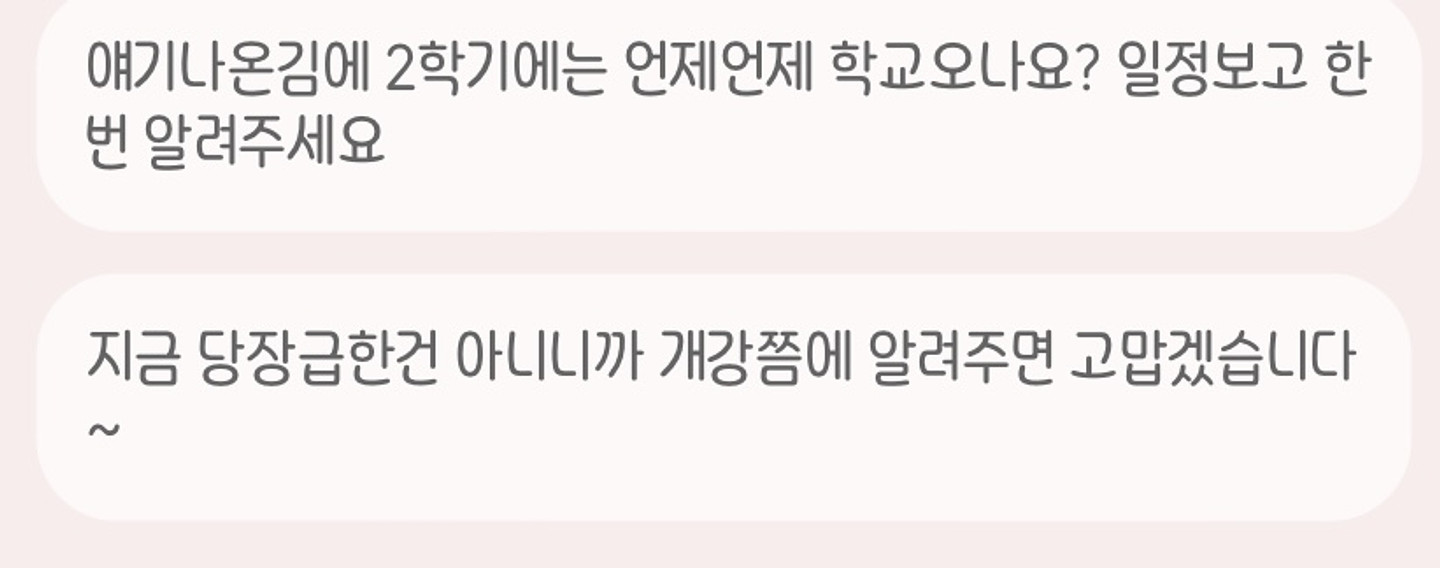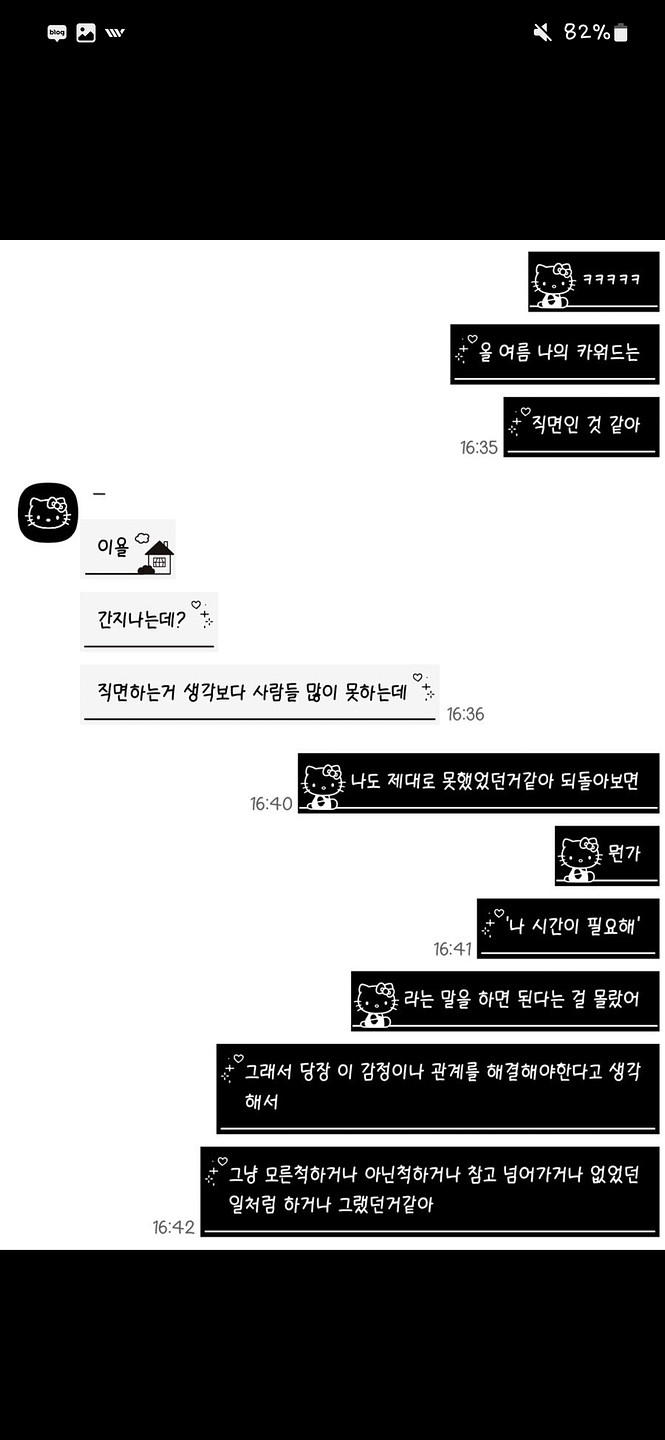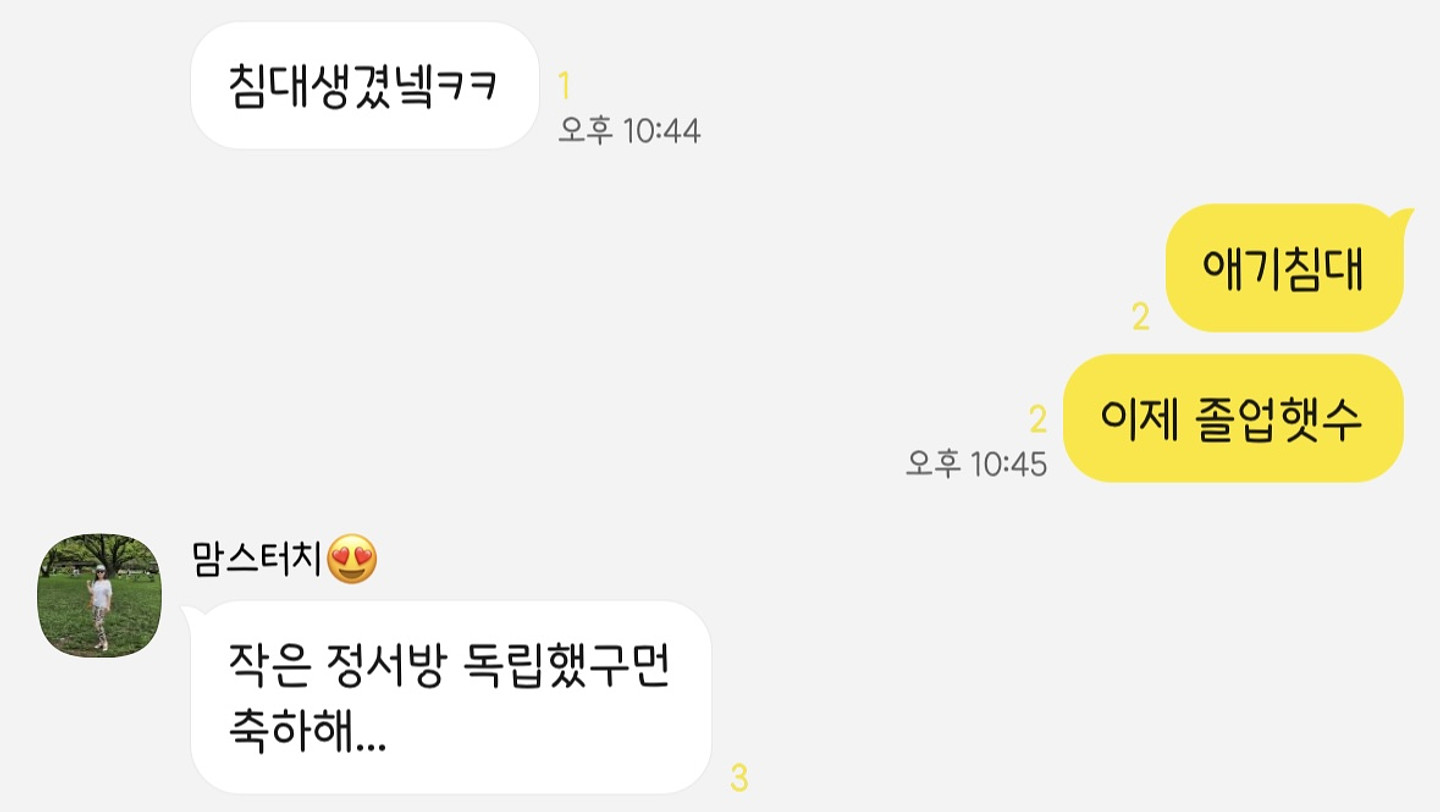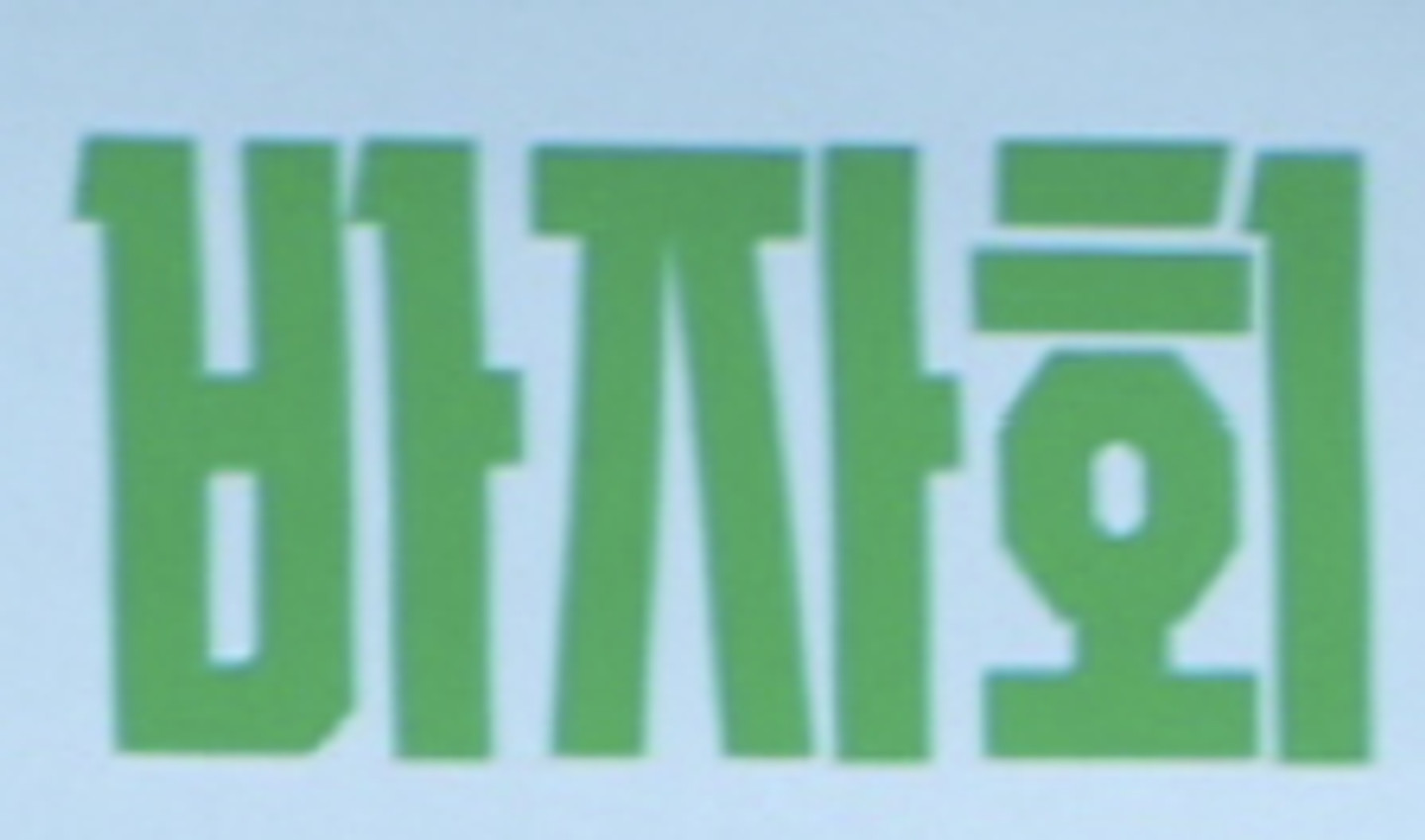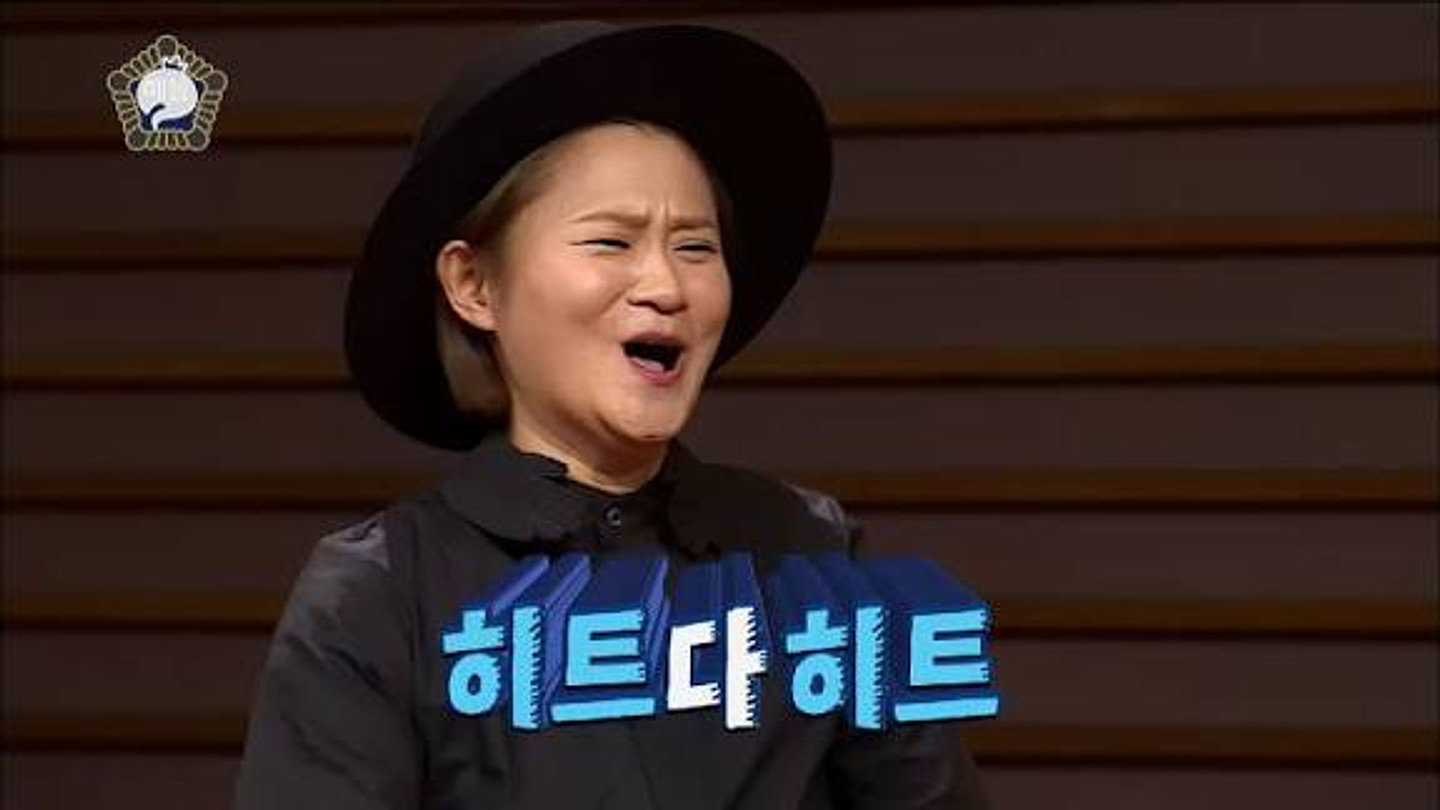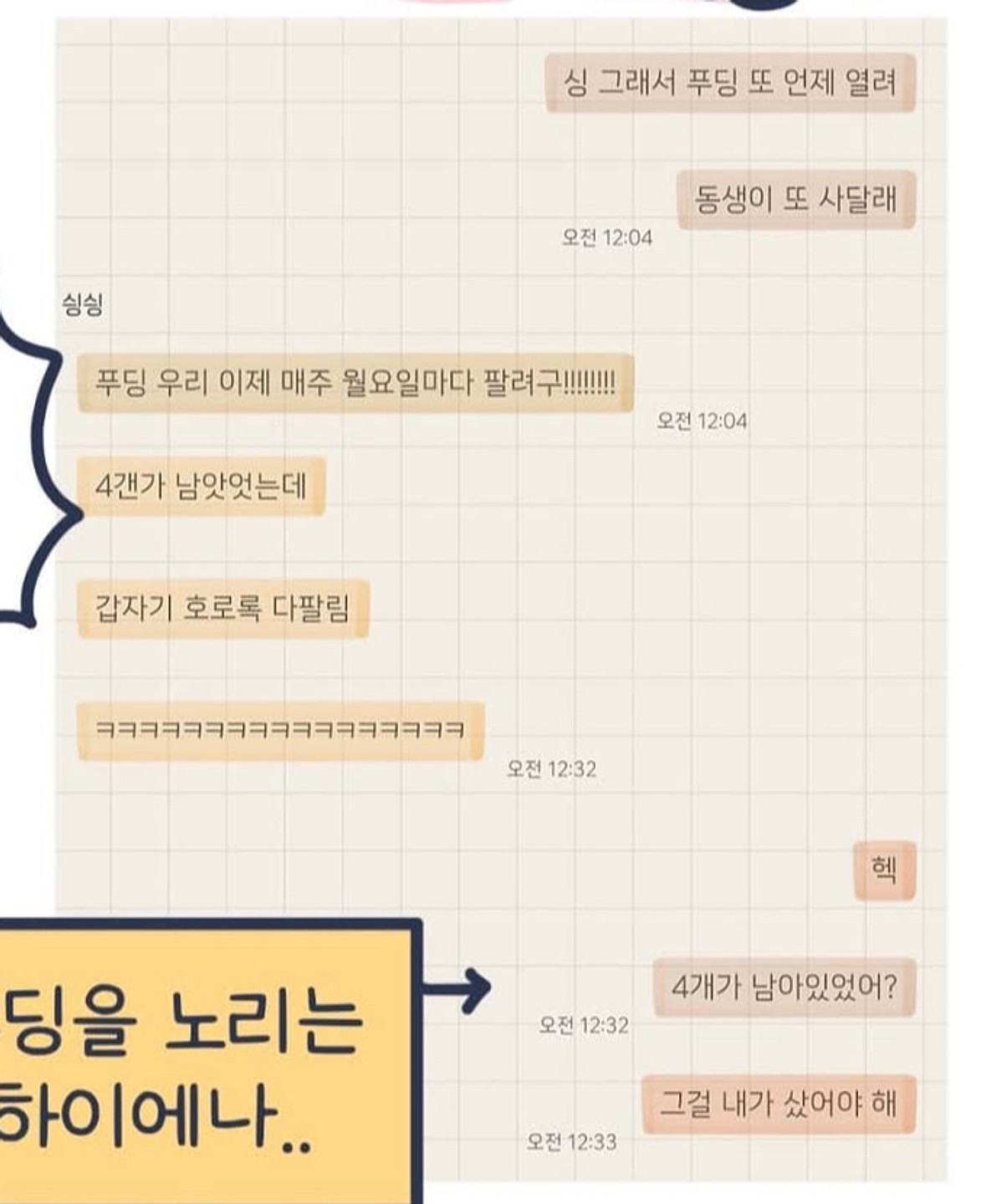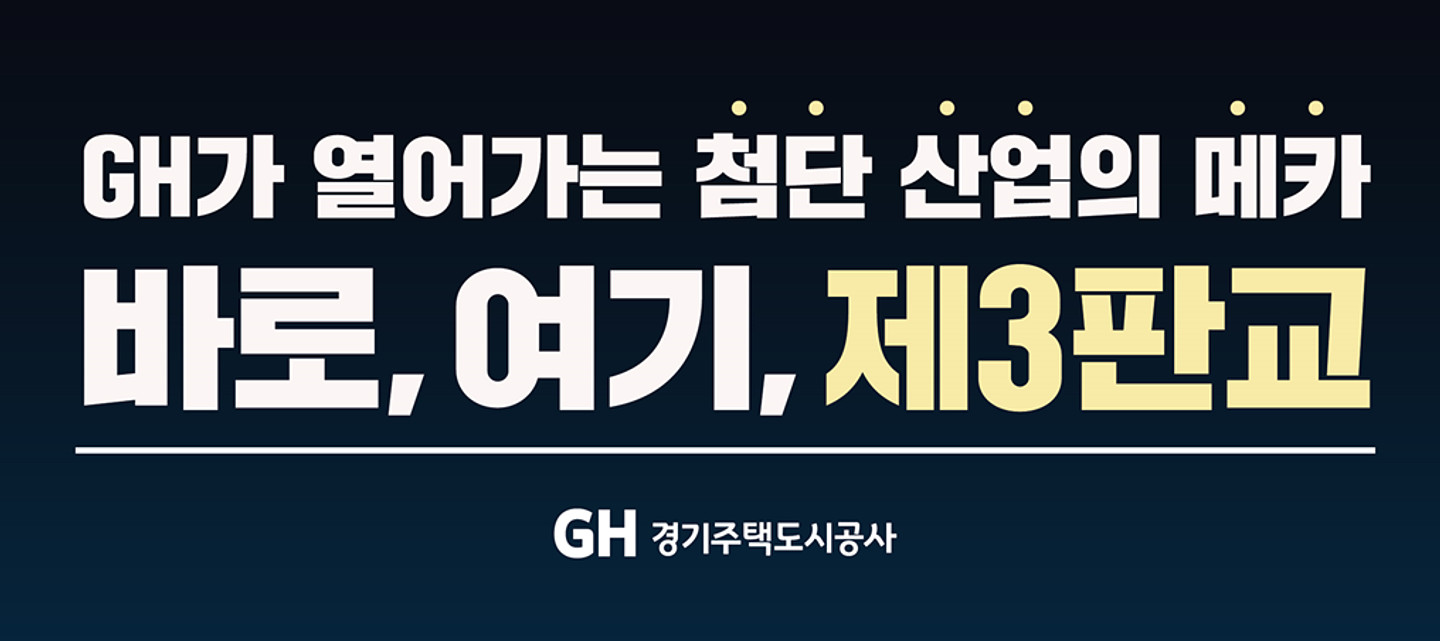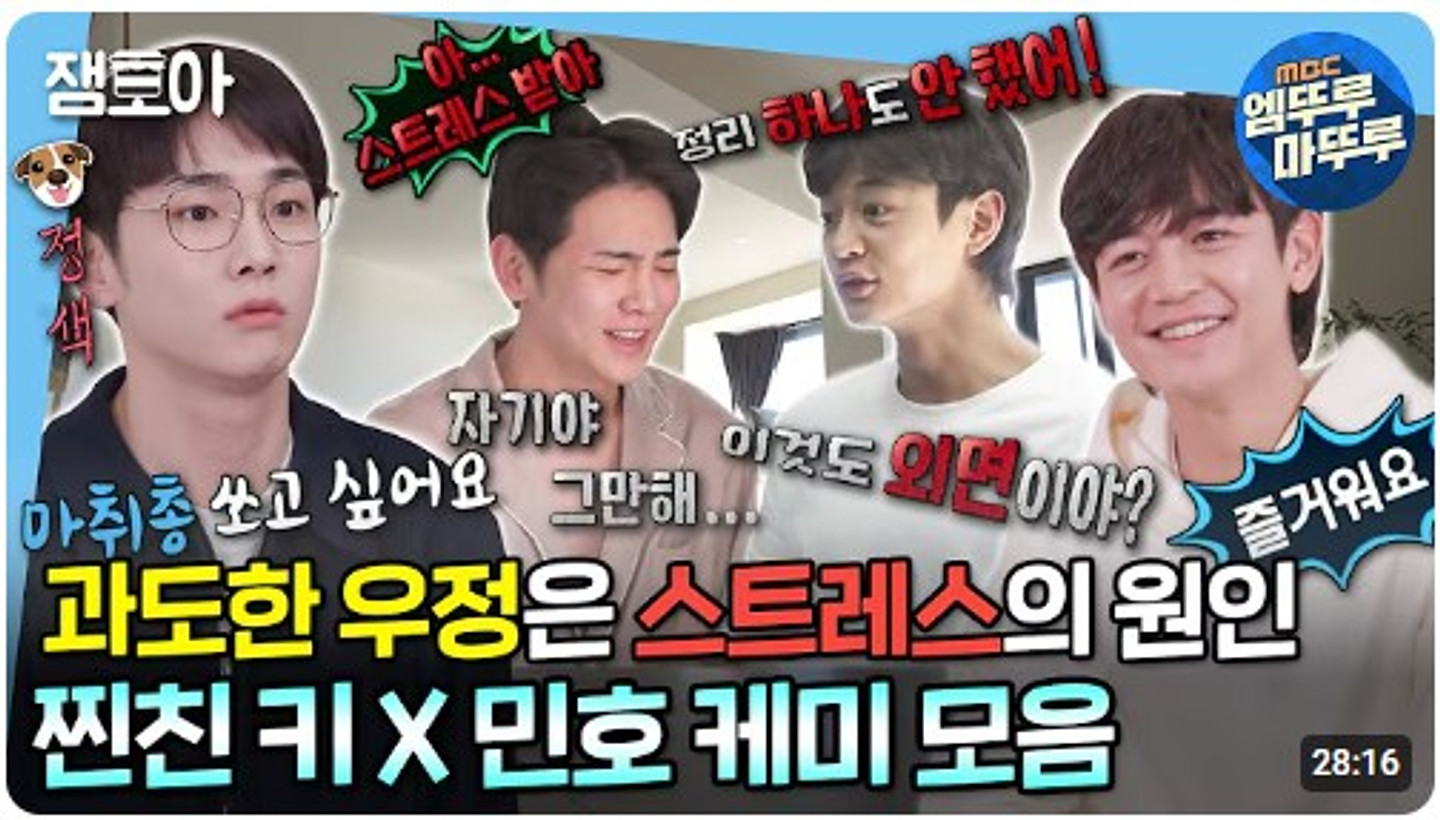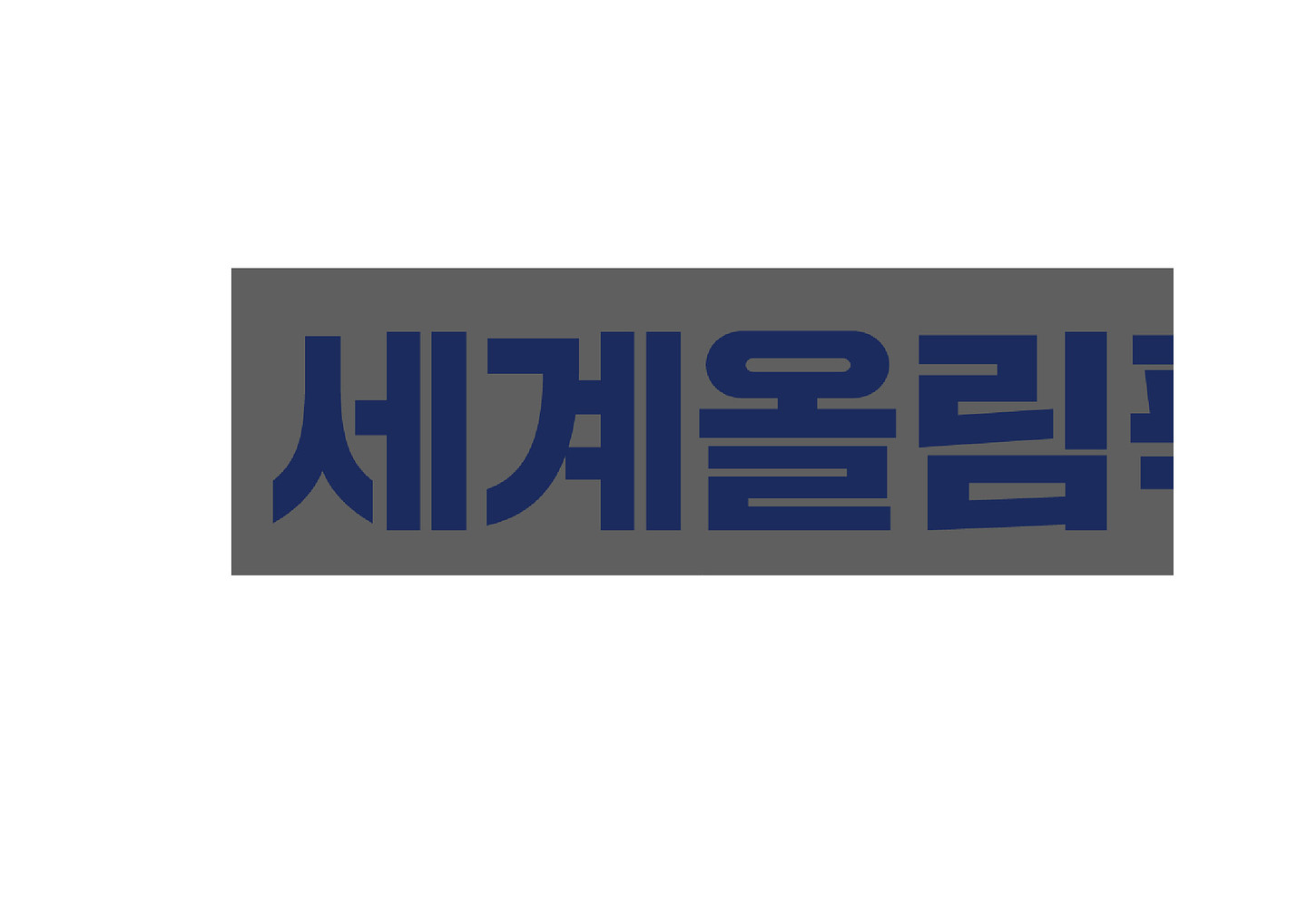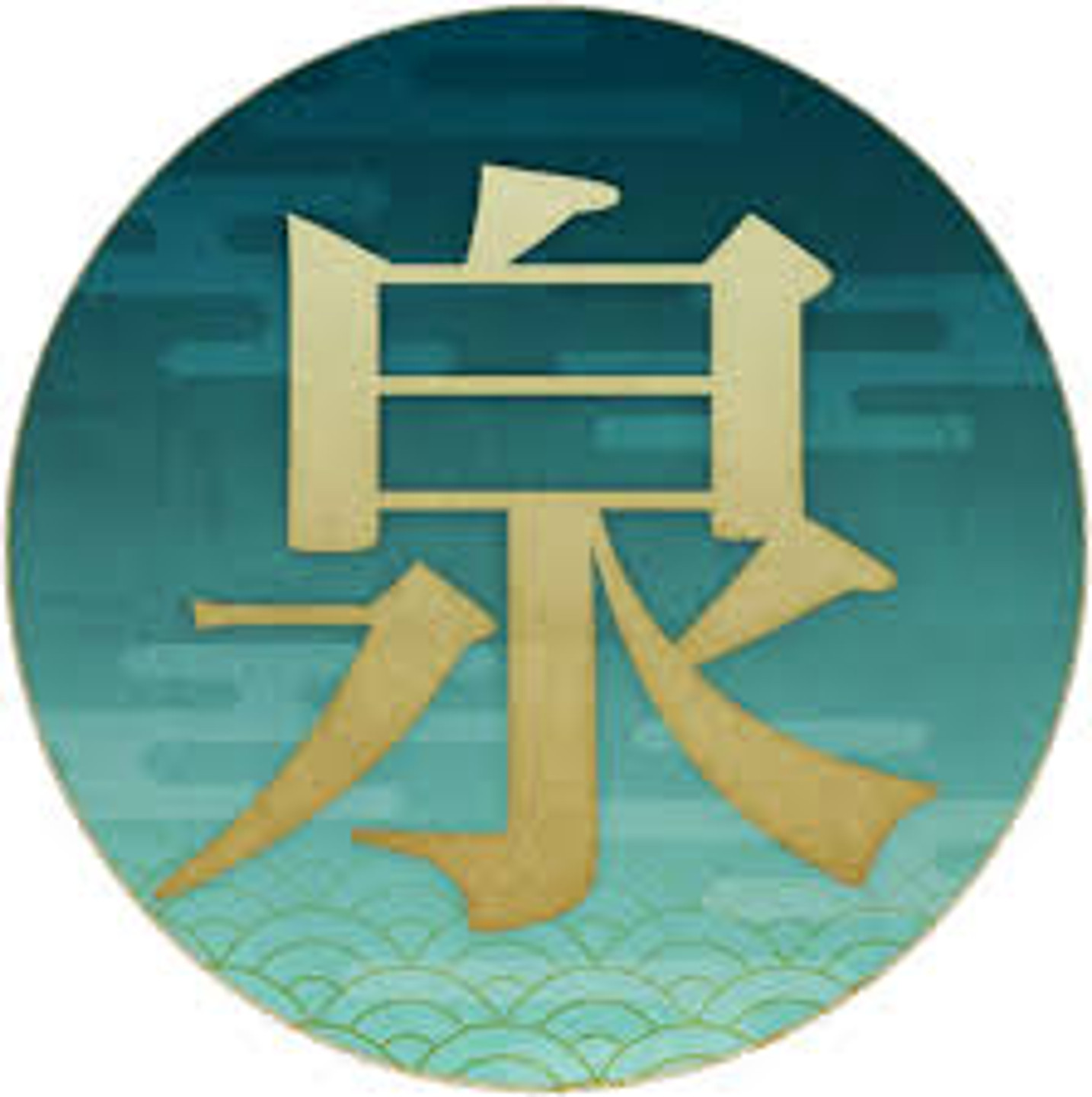
폰트 뭔지 알 수 있을까요?
저 파란색 글씨 서체가 뭔가요?
안녕하세요 지피티가 만들어준 글씨체인데 이런 글씨체 혹시 존재할까요~?
네온 작업된 서체인데 비슷한 서체도 추천부탁드립니다
이 폰트 무엇인가요?
어떤 폰트일까요? 궁금해요 !!
유튜브에서 봤어요
국보온돌침대 폰트 기존 있는 폰트인가요? 기존 있는 폰트를 본거 같기도 하고.. 고수님들 알려주세요
무슨 폰트인가용
그 제작자의 손글씨잉가 했는데 종종 본 것 같어서요 뭘까요?
요거 어떤 폰트 인지 아시는 붐
뭔가 어린아이 폰트?? 이런 느낌의 이름이였던 걸로 기억하는데... 제발 알려주세요!ㅜㅜ
이 폰트 뭐에여 인스타에서 검색할때 가끔 뜨던데 ㅠ
폰트명이 궁금해요.
사진속 기사 폰트가 뭘까요?
안녕하세요! 이 폰트가 무엇인지 아시는 분 계실까요?
위에 굵은 폰트와 아래 작은 폰트 뭘까요?
이 폰트 정보가 뭔가요?
이 폰트 뭘까요? ㅜㅜ
이거 무슨 폰트인지 아시는 분...ㅜㅜ
오늘도 사랑해 에 들어가는 폰트 궁금해요
사진 속 폰트가 궁금합니다.
이거 벌써 삐져있다 ㅋㅋㅋㅋ 이 멘트 무슨폰츠에요 ㅈㅂ
"음악이 삶의 전부는 아닙니다만" 이라는 책의 본문에 쓰인 폰트인데 어떤 폰트일까요? 여러 방면으로 이미지 검색해봤는데 못찾았습니다 ㅠㅠ --- 우와 폰트박사이신가요ㅠㅠ!!!!! 정말 감사드립니다!! 댓글 다는 곳이 없어서 이렇게 감사인사 남겨요
이폰트도 궁금합니다
폰트 뭔지 알 수 있을까요ㅠㅠ
글꼴이 궁금합니다
폰트 뭔지 알수있을까요ㅜㅜ
혹시 이폰트가 무슨체인지 알수 있을까요
이런 길고 빈티지스러운 영어폰트 비슷한거라도 괜찮으니 찾고싶어요!
서체 이름 알고싶어요~
이 폰트가 뭘까요? 세로로 긴 폰트입니다..!
여기에 사용된 폰트가 뭘까요!! 아무리 찾아도 안나오네요..! 왠지 기존 폰트를 변형해서 사용한 것 같기도 한데!! 고수분들 부탁드립니다!
이거 무슨 폰트일까요ㅠㅠ 핑크색이욤
무슨 폰트일까요? 무료 폰트가 아니면 가장 비슷한 무료폰트 있을까요?
이 이미지 속 폰트들은 어떤건가요?
글꼴알려주세요ㅠ
유튜브 '아무튼 떠들러 왔는데' 폰트 뭘까요? 비슷한 글씨체는 나오는데, 완전 똑같은 폰트는 못 찾겠네요 ㅠㅠ
이거 무슨폰트인지 아시는 분 있을까용,..
'청옥션갤러리' 이 폰트 뭘까요?
이런 색연필로 쓴것같은 느낌의?? 폰트 너무 궁금해요ㅠㅠ
폰트궁금해요
썸네일 폰트가 뭘까요 ㅠㅠ
(자체 해결 완)화질이 좀 깨지긴했지만.. 비트로 인스파이어랑 유사하긴한데 혹시 아시는 분 계실까요?
이건 무슨 폰트일까요? ㅜㅜ
한번 더 올립니다.. 캡컷 3.3.0.1161 버전으로 이 폰트 어떻게 내나요..?
이거 원래 폰트가 뭘까요...?
폰트찾습니다,아시는분 계실가요,, 부탁드립니다.
손으로 쓴건가 싶기도한데..뭘까요
폰트가 이쁜데 궁금합니다
요 폰트 대체 뭘까요...되게 보편적인것같아서 대입해보니 맞는게 없네요...고수님들 도와주세요...ㅠㅠ
보이넥스트도어 자체콘텐츠 자막
이거 폰트 뭘까요..?